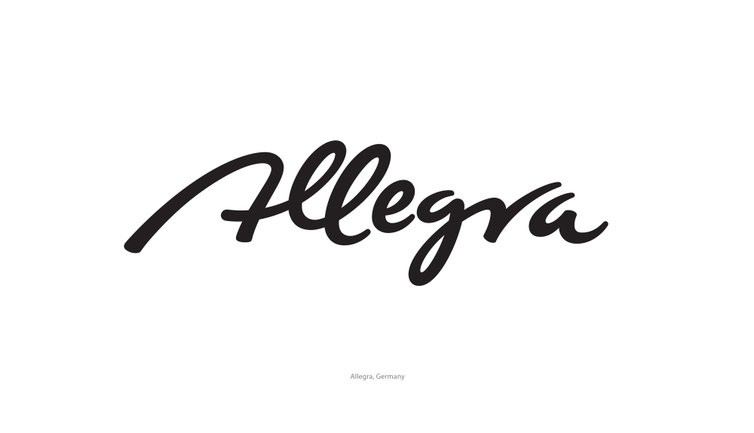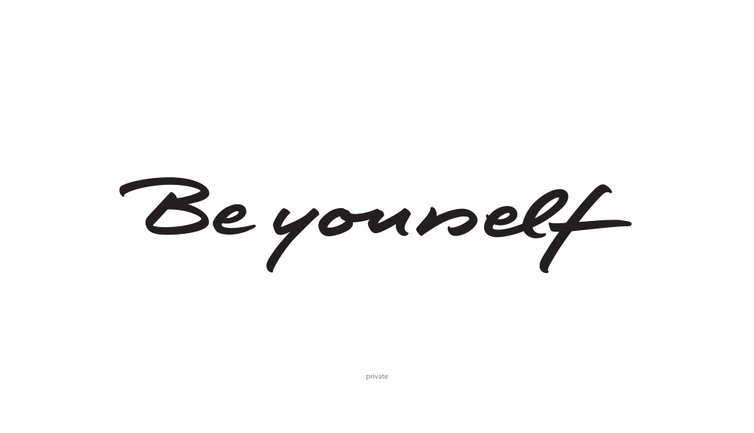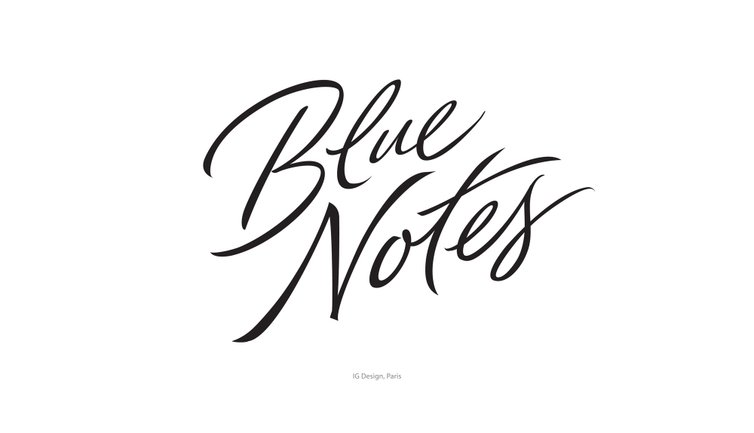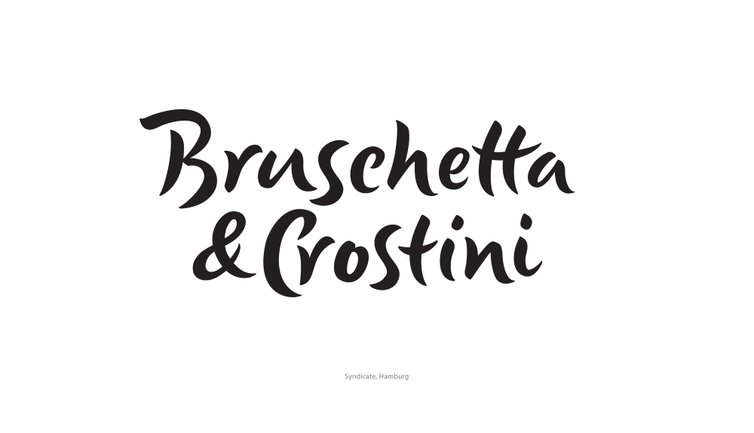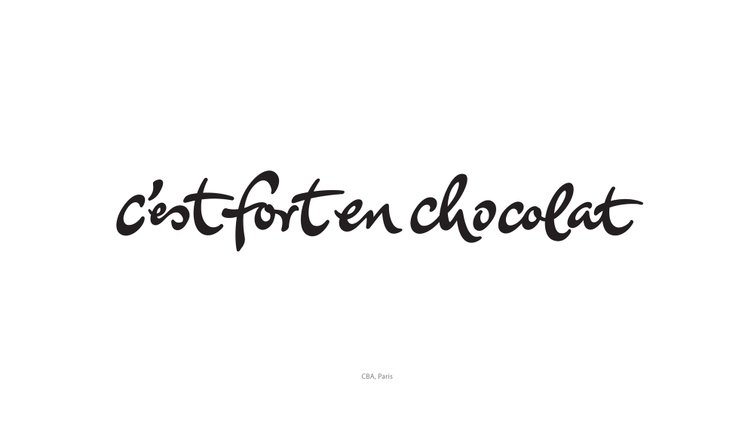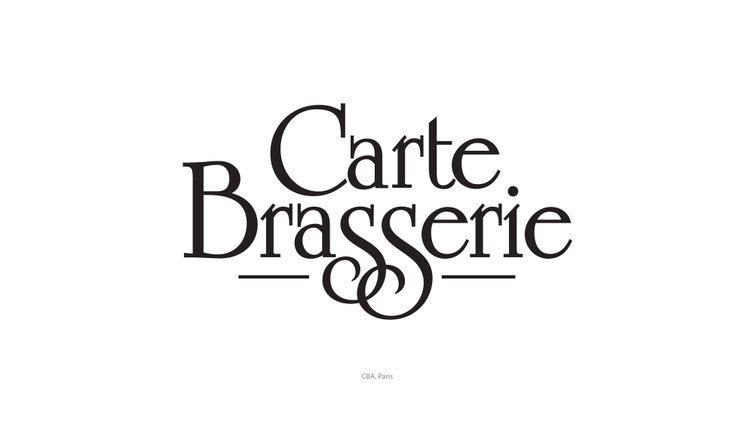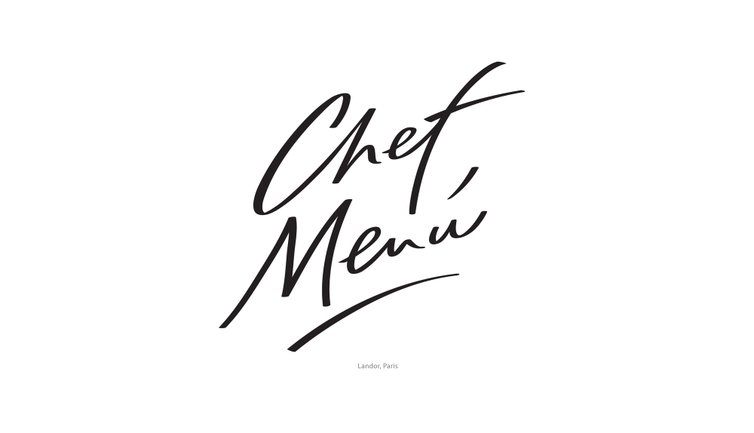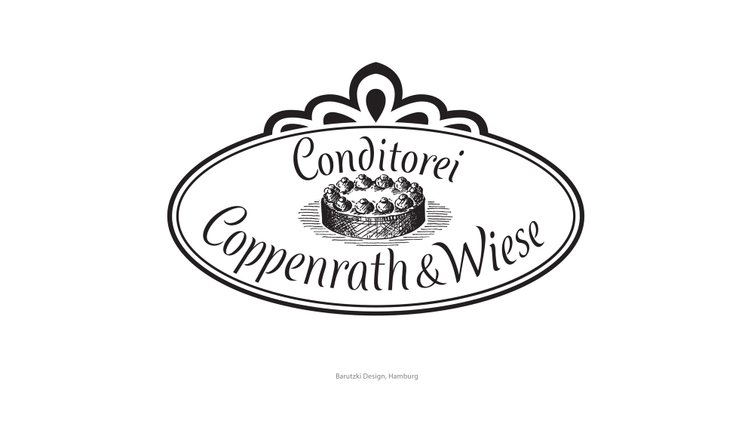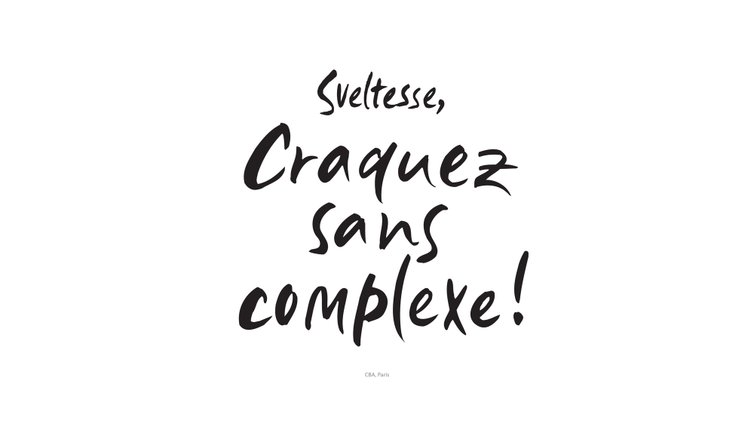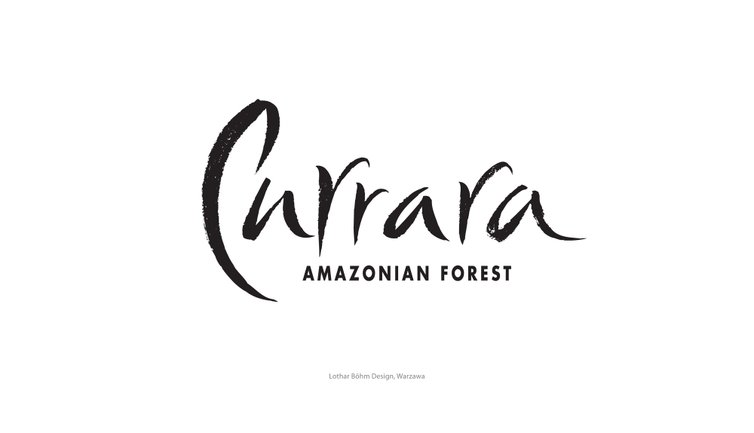
Calligraphe
Lettering Artist à ()
Au fil d'une longue et belle carrière de Calligraphe et de Lettering Artist, Peter a produit certain des logos les plus iconiques de nos vies quotidiennes. Doté d'une grande culture typographique et d'un savoir-faire incontestable, Peter parvient à créer, avec une rapidité déconcertante, des logos qui perdureront, sans prendre une ride, pendant des décennies.